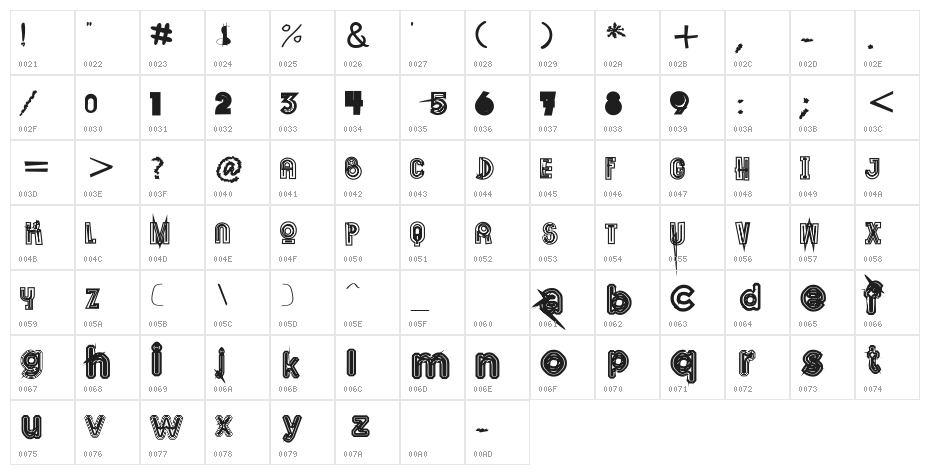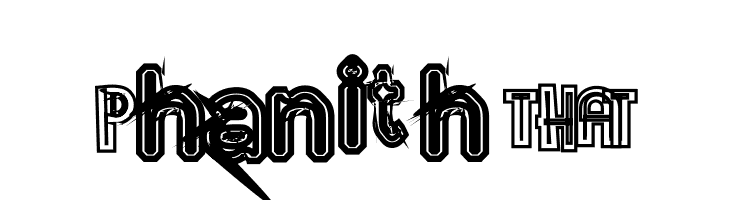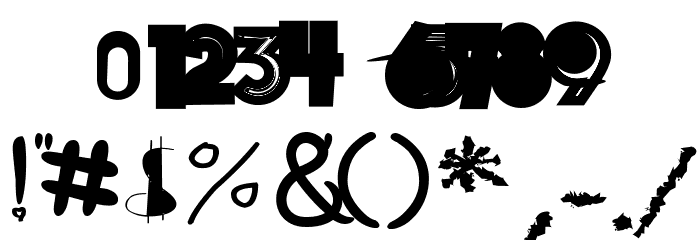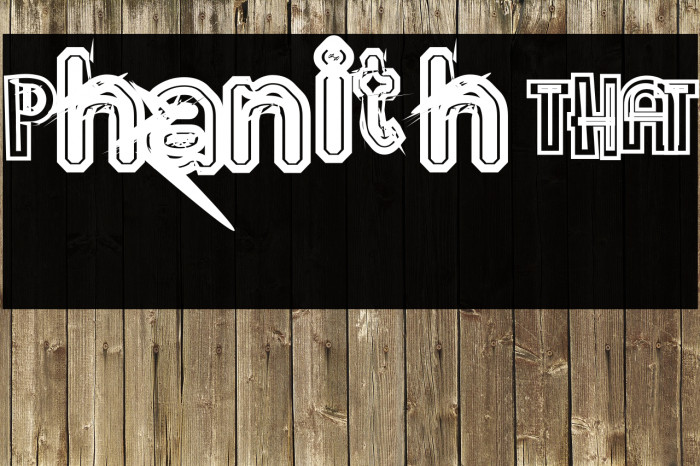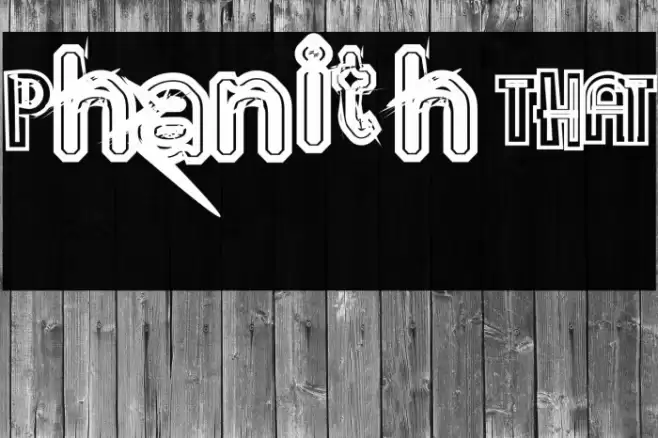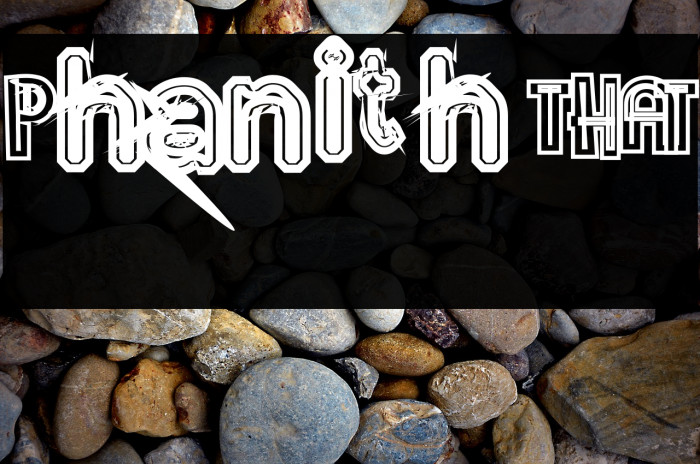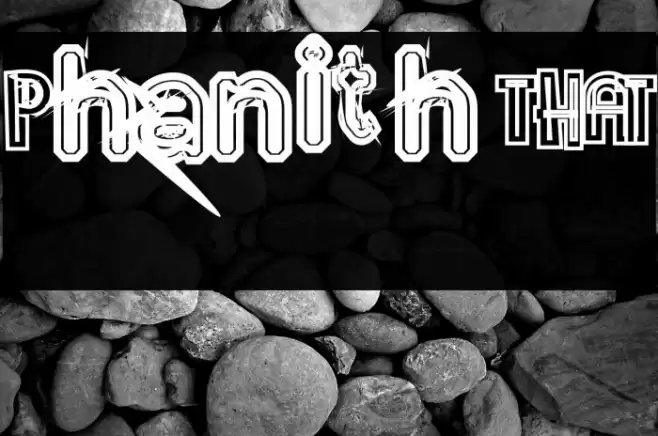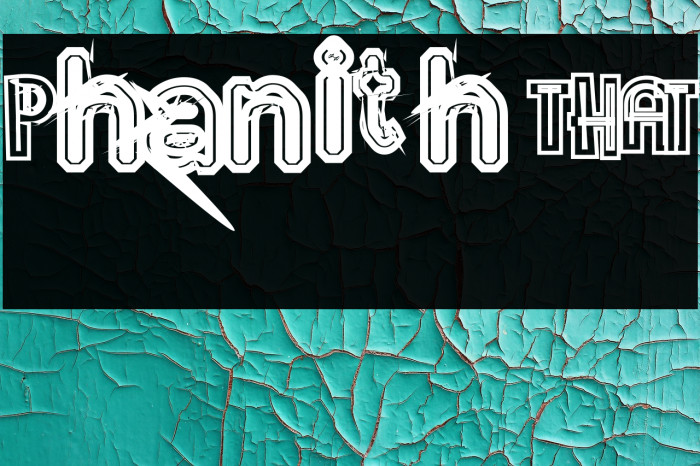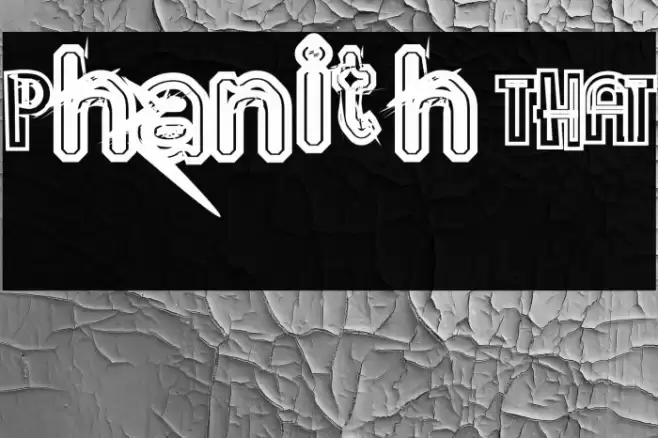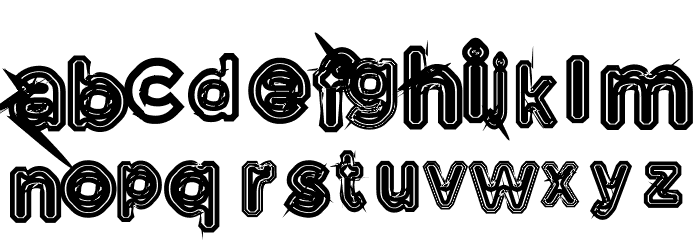
Phanith THAT Font
✎ Thick
| श्रेणियाँ | Thick |
| कंट्रास्ट | High |
| समग्र शैली | Decorative |
| उपयोग का मामला | Headlines, Logos, Posters |
| सुझाए गए प्रोजेक्ट | Ideal for Halloween-themed designs, posters, album covers, and any project needing a striking, unconventional look. |